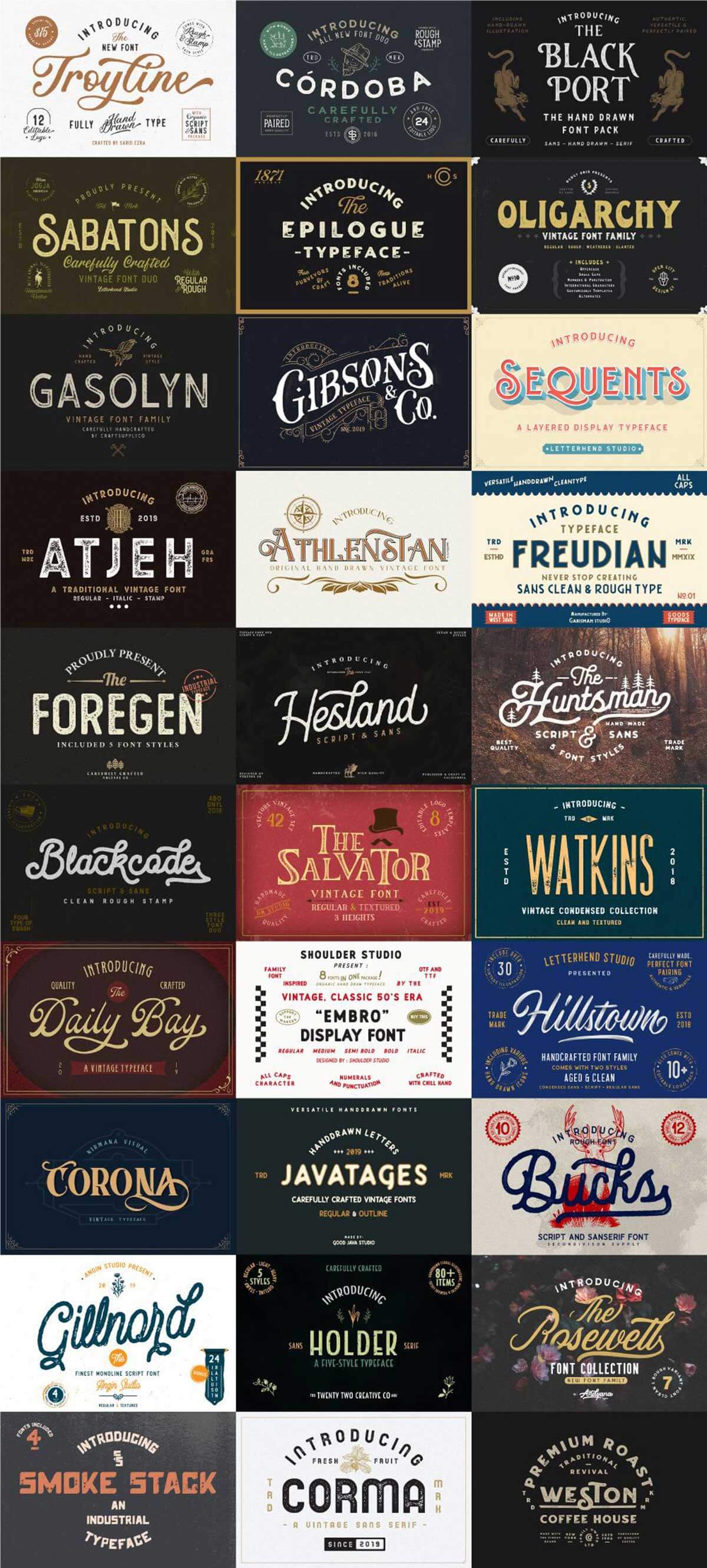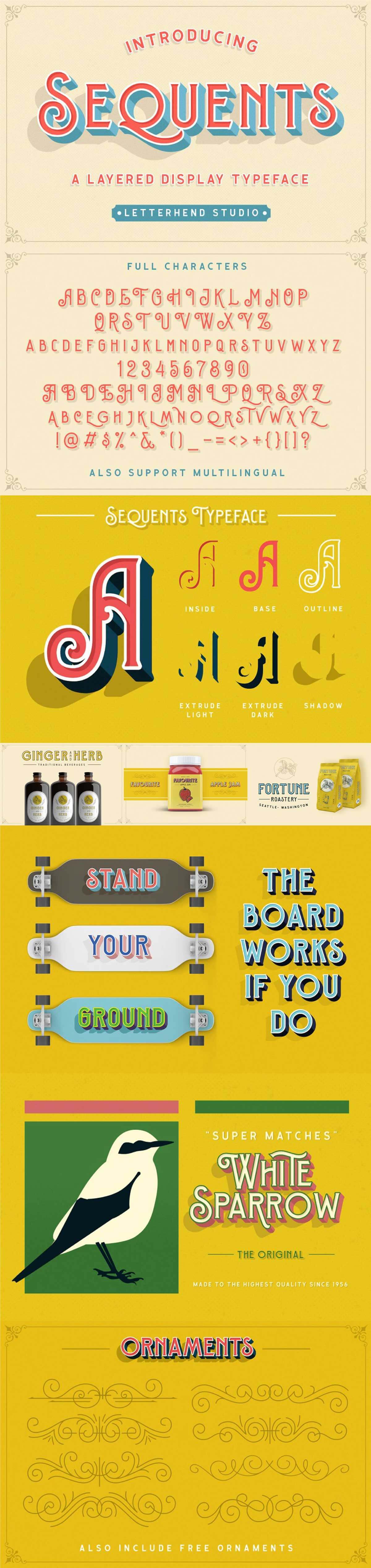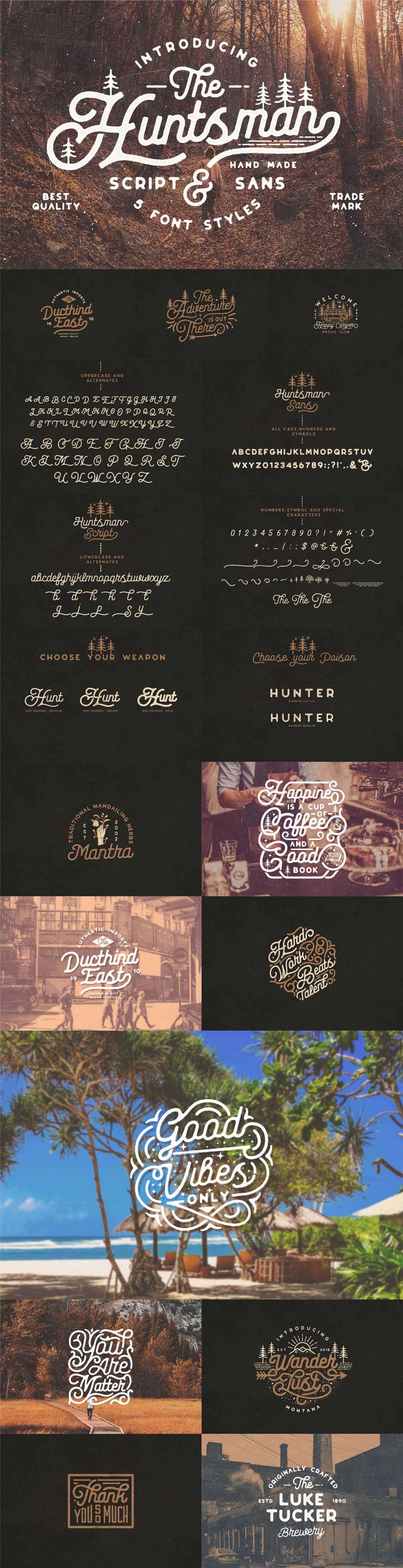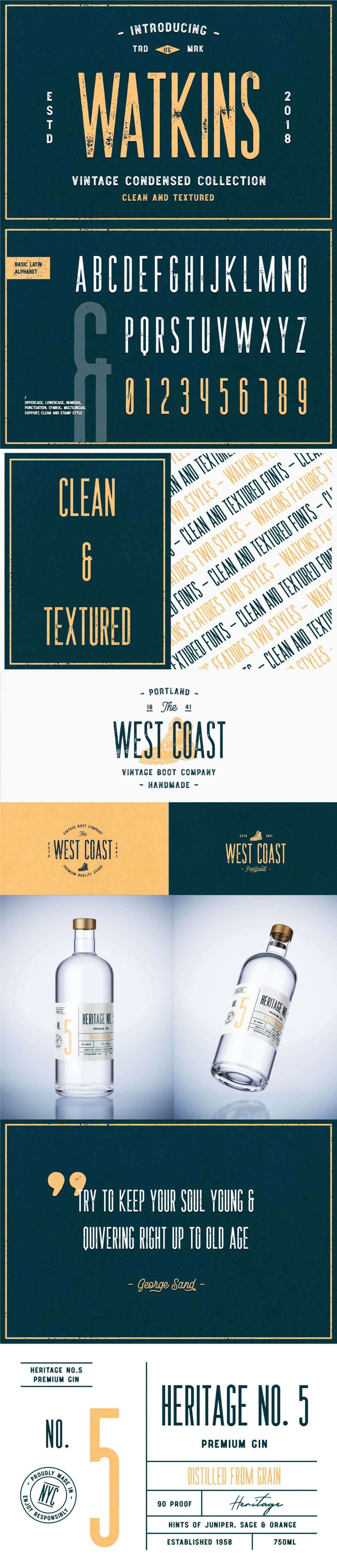
Pixel Surplusでは、かすれ風テクスチャ加工済みの書体が含まれたセットを29種類収録したフォント集「The Rustic Font Bundle(ザ・ラスティック・フォント・バンドル)」が一ヶ月限定販売中です。
わざわざPhotoshopなどでかすれたように加工する必要がないので、とてもラクですよ。ほとんどのセットには、かすれ加工なしのクリーンなフォントも収録されています。
「The Rustic Font Bundle」の気になる中身
今回のバンドルの中で、私が特に気になるフォントはこちらです。
The Huntsman – NEWFLIX.Bro
かわいい雰囲気で親しみやすいスクリプトフォント。ウェイトが3種類用意されているので、デザインを細かく調整できます。飾りもたくさん用意されていますよ。
Hillstown – Letterhend
「Hillstown」は、ロゴ作成がはかどるロゴテンプレートとアイコンデータつきのフォントセットです。これさえあれば味のあるロゴが簡単に作成できますよ。
Watkins – Pixel Surplus
Pixel Surplusオリジナルフォント「Watkins」は、2019年4月現在はPixel Surplusでしか購入できません。ユニークなフォントを探しているなら、ぜひ使ってみたいですね。
Sequents – Letterhend
影やアウトラインなどを組み合わせるだけで、ちょっと難しそうに見える立体的なロゴも簡単にできあがる「Sequents」。オーナメントも付属していますよ。
このほか役立つフォントばかり合計29セットを収録しています。この記事で紹介できなかった書体はぜひ詳細ページから確認してくださいね。